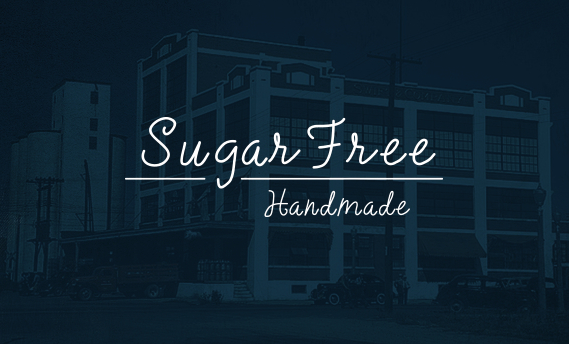
SugarFree Handmade Font
A SugarFree é uma fonte de script feita à mão com linhas bases variáveis, projetada para transmitir elegância e estilo. Seu charme autêntico se destaca em diferentes formatos, tornando-a perfeita tanto para aplicações visuais elaboradas quanto para t-shirts criativas. Seja para headlines, logomarcas, convites de casamento, etiquetas de produto, cartazes, selinhos ou até mesmo letras de notícias, SugarFree oferece aprimoramentos de estilo OpenType para maior personalização e flexibilidade. Para aproveitar ao máximo os recursos de styling desta fonte, é necessário um programa que suporte as características do tipo aberto como Adobe Illustrator CS, Adobe InDesign ou CorelDraw X6-X7. Experimente SugarFree para dar vida a seus projetos com um toque autêntico e sofisticado.